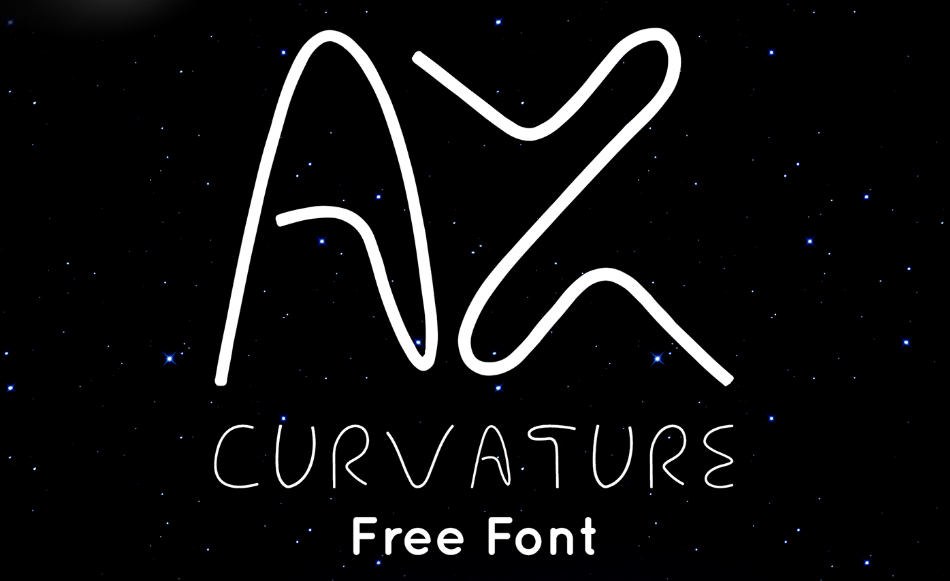
AX Curvature Font – Download Grátis
A fonte AX Curvature é uma mão-dura criada pelo designer Hamilton que se destaca por sua naturalidade e autenticidade. Suas linhas fluidas e sutis refletem a essência de uma escrita casca, oferecendo tanto um toque moderno quanto uma conexão direta com as fontes tradicionais da caligrafia. A AX Curvature é perfeita para aplicações em marketing digital, design editorial e criação de arte digital onde o formato elegante e único pode dar um grande impulso à sua marca ou projeto. Ideal tanto para designers profissionais quanto para criadores aficionados que desejam incorporar uma textura única e vibrante ao seu trabalho.